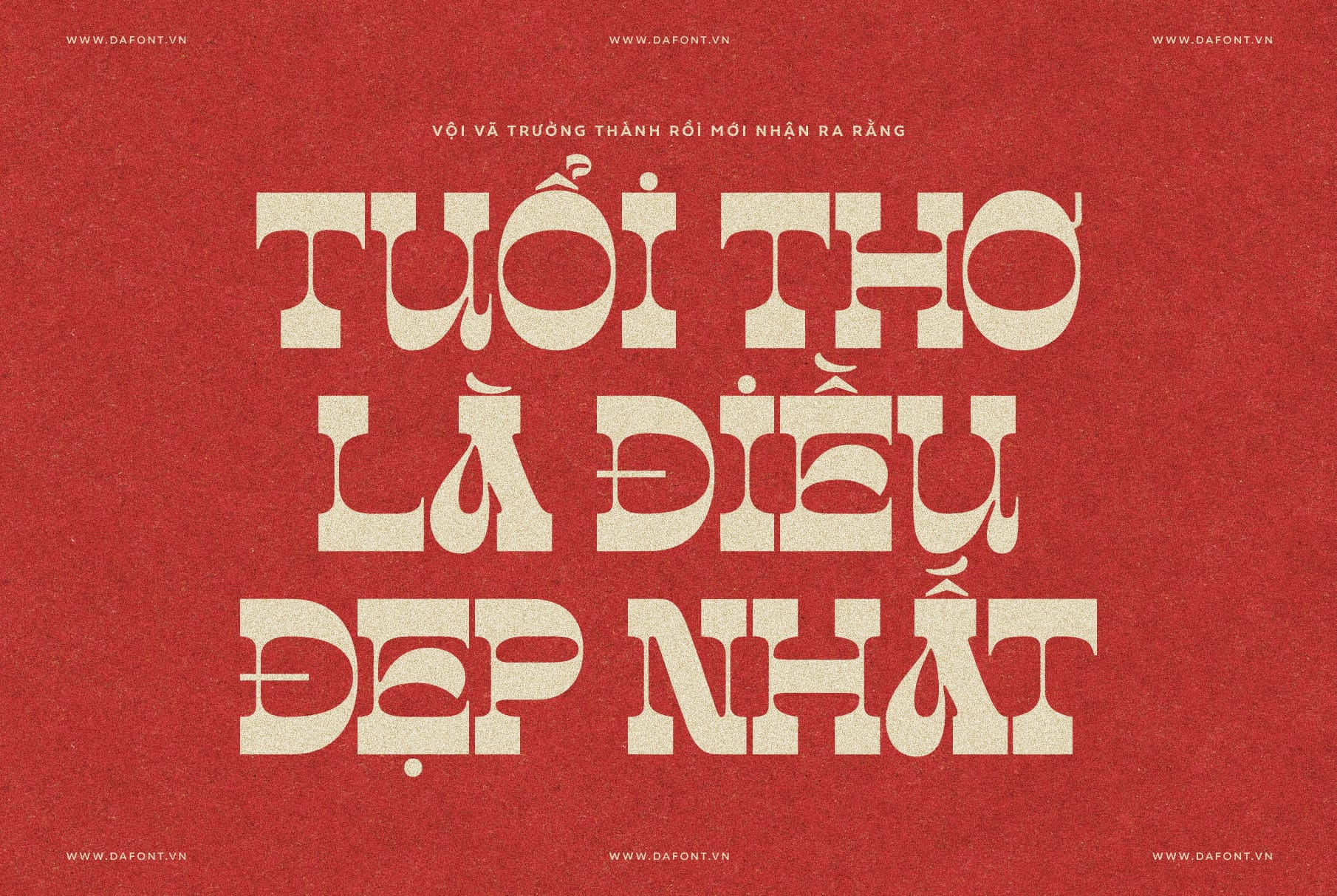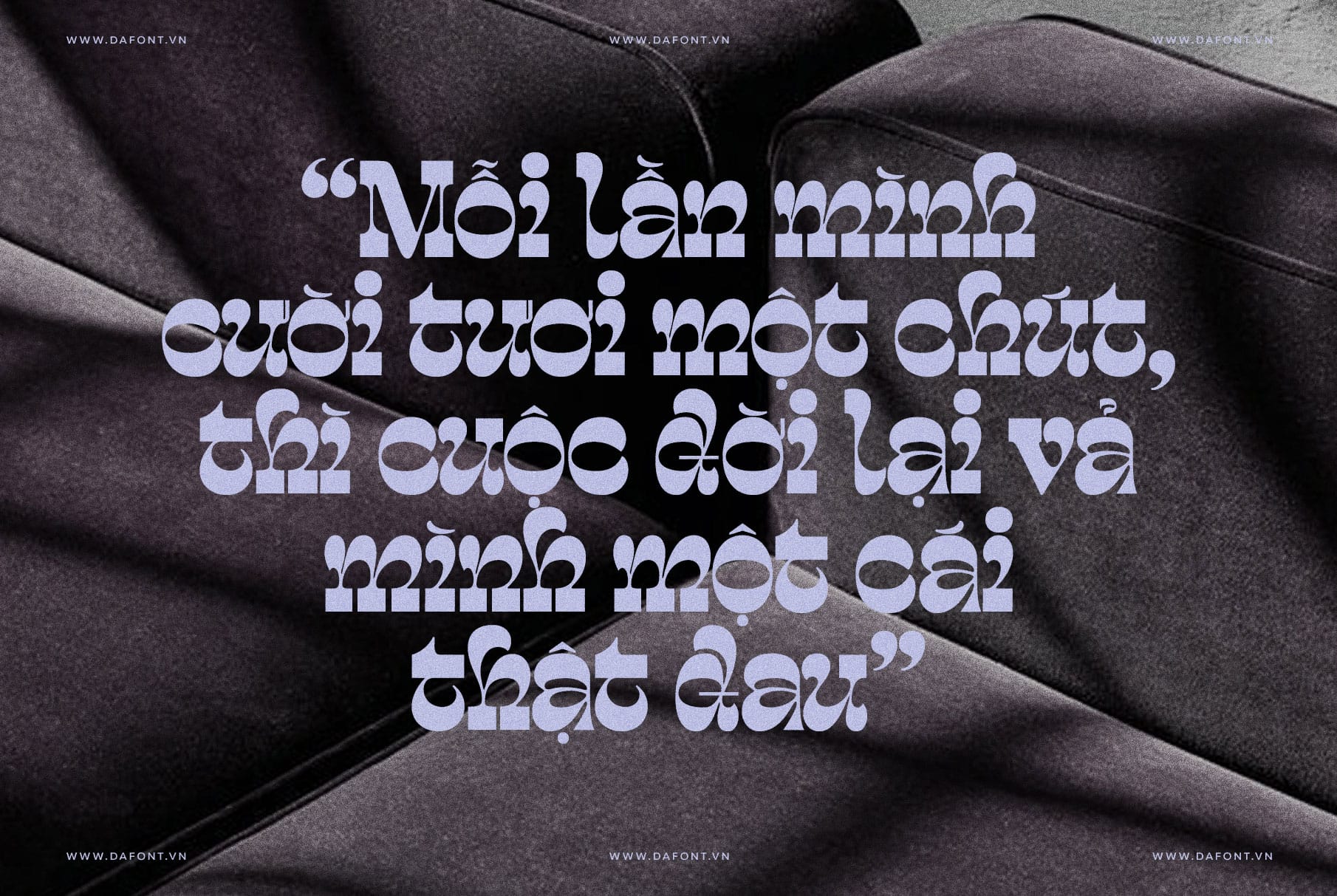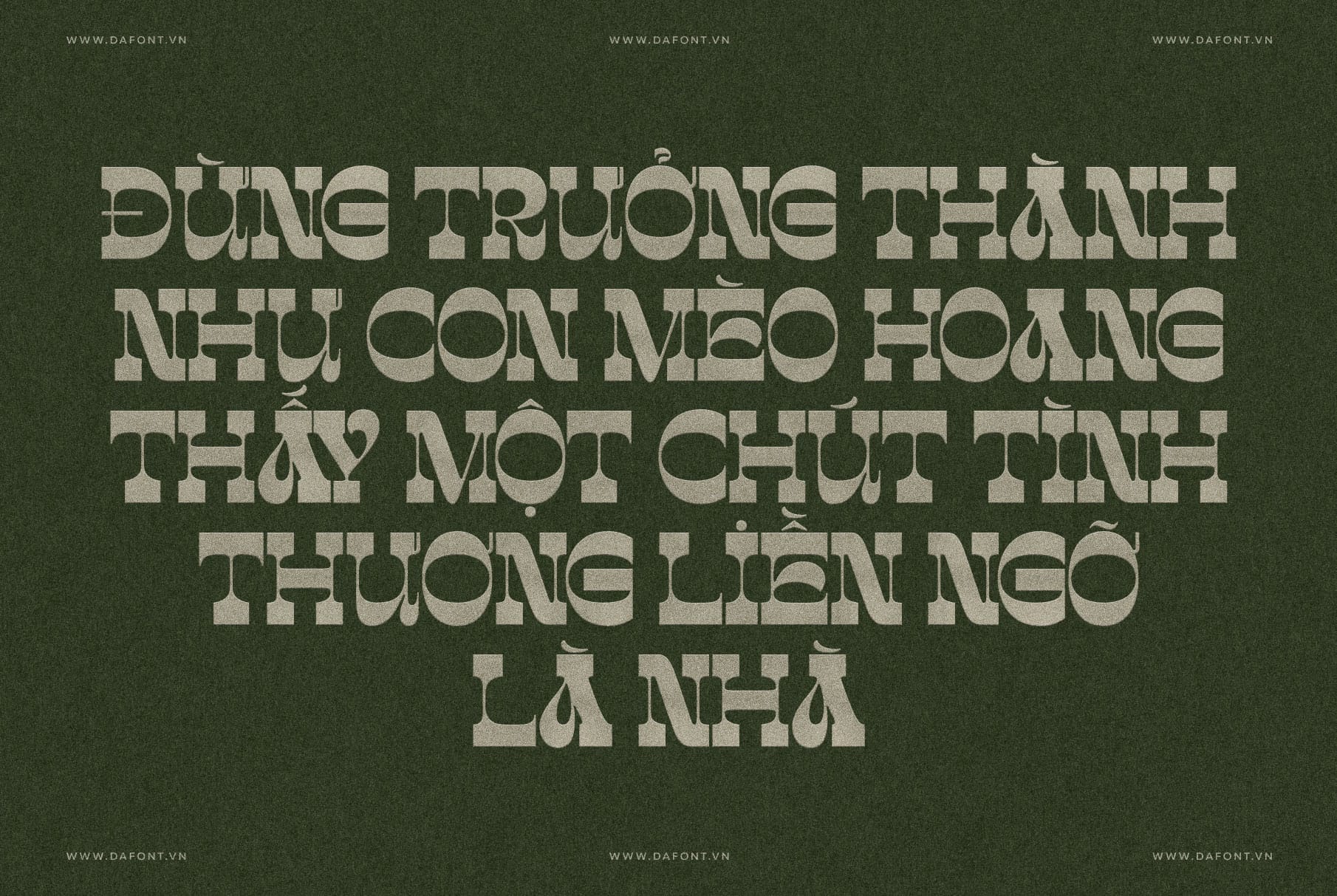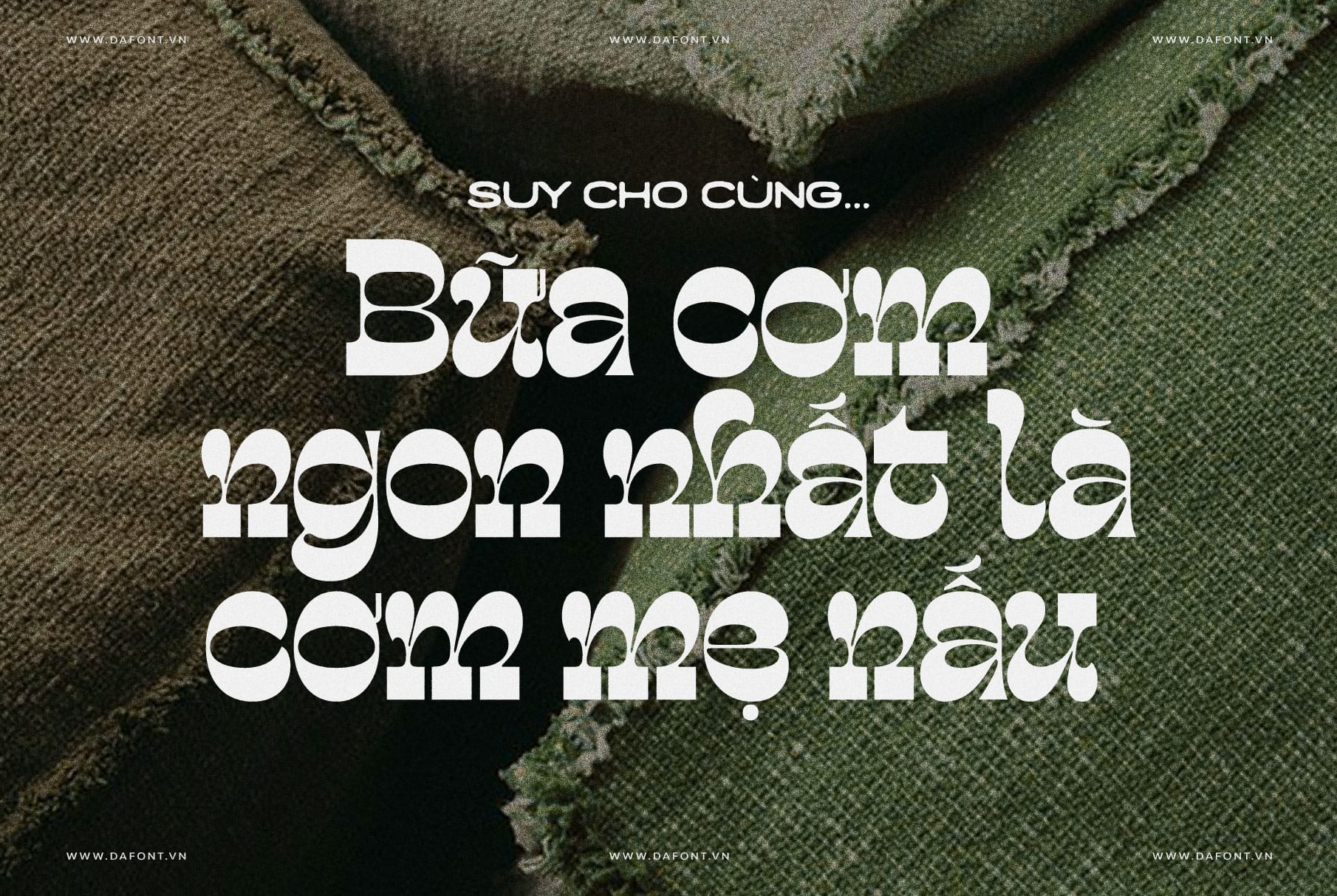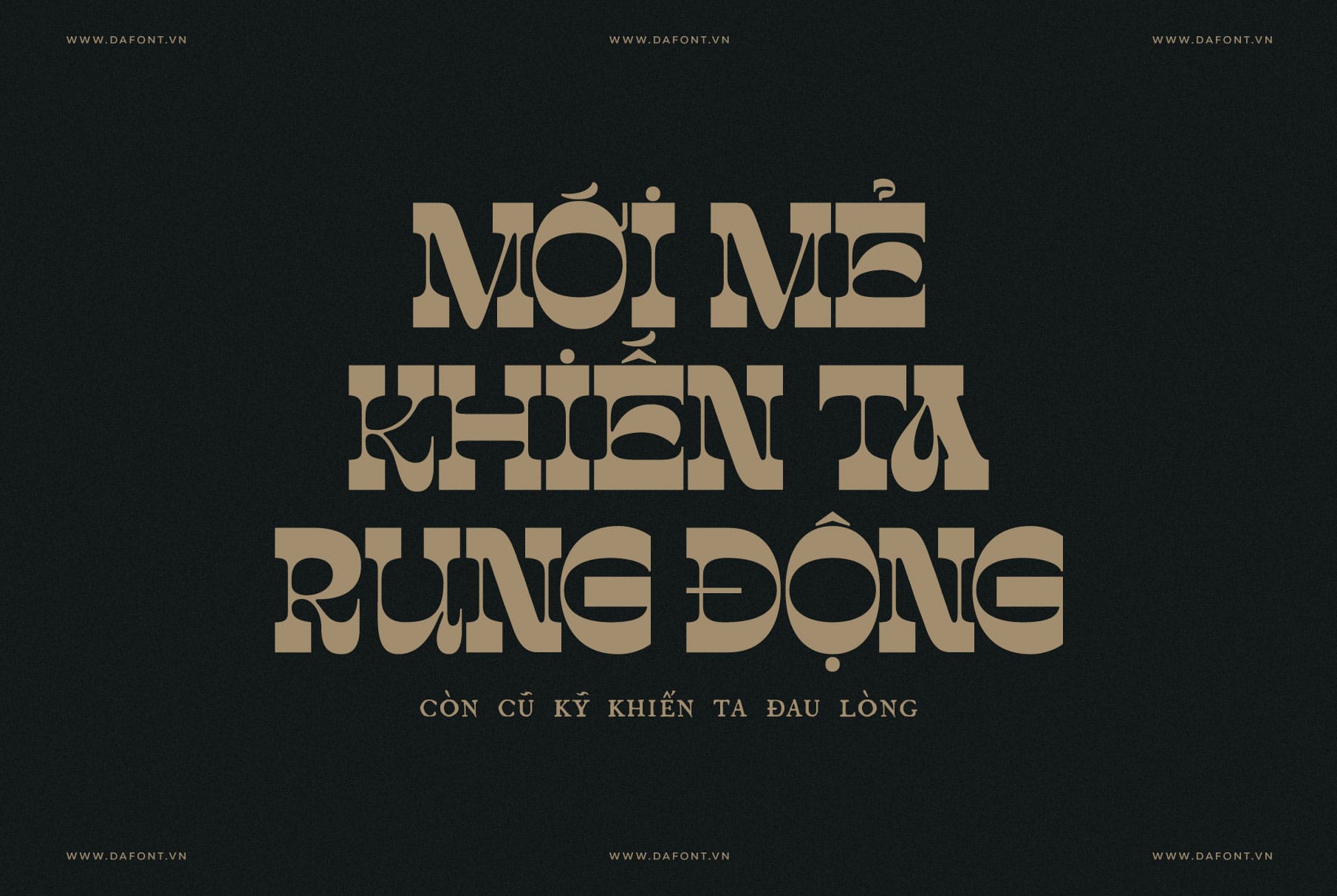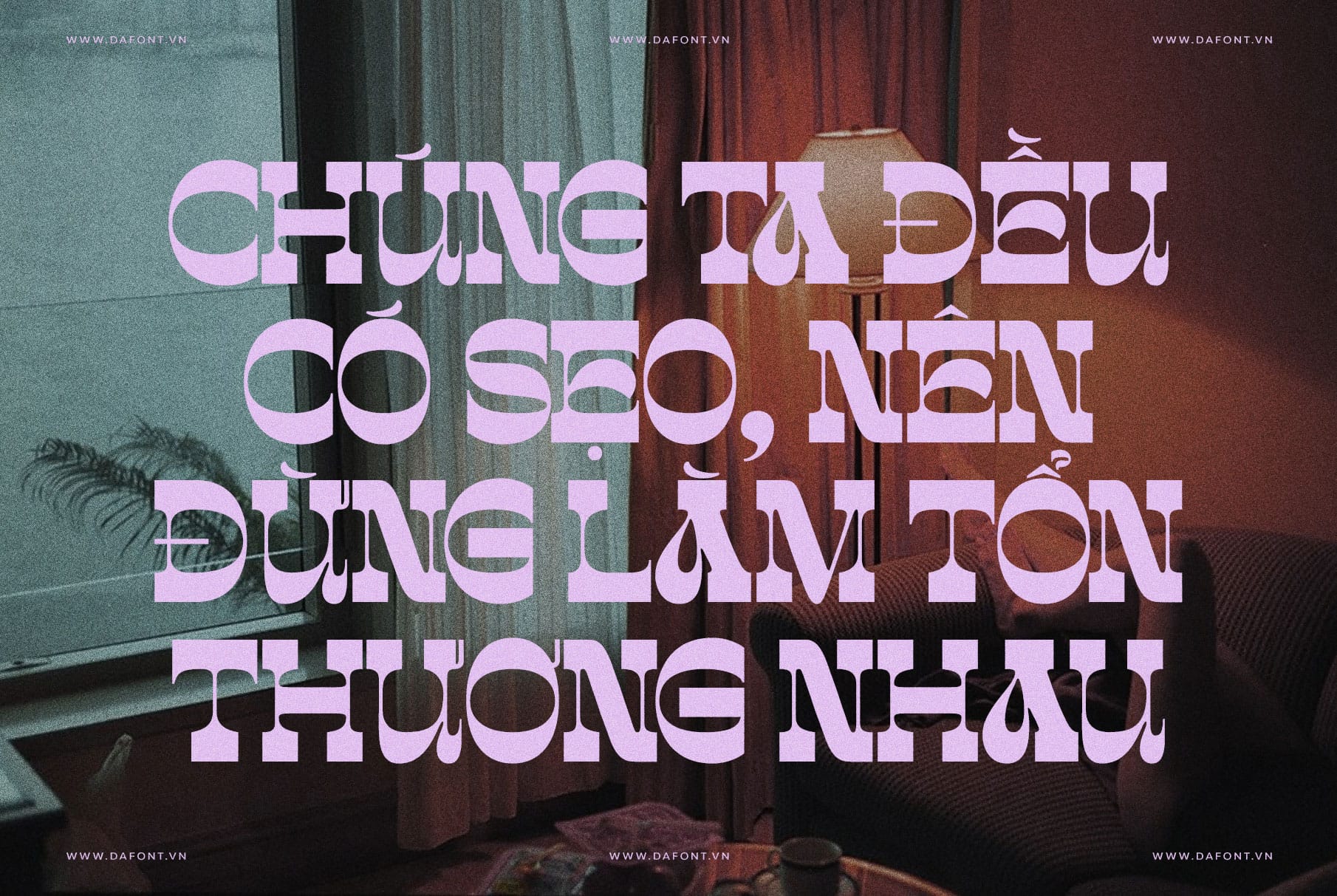
DFVN TAN – MADISON
Kiểu khữ slab serif retro đầy cá tính cho thiết kế hiện đại
DFVN TAN – MADISON font thuộc loại slab serif – kiểu chữ với nét serif vuông vức, dày dặn, tạo cảm giác mạnh mẽ và vững chãi. Điều làm nên sự khác biệt là các đường cong playful (vui tươi), mang đến sự bất ngờ và cá tính. Font gợi nhớ đến văn hóa Mỹ cổ điển: quán soda, đĩa vinyl, hay bưu thiếp du lịch, nhưng vẫn giữ nét hiện đại để phù hợp với branding ngày nay.
Đặc điểm nổi bật DFVN TAN – MADISON
TAN – MADISON là một kiểu chữ slab serif mang đậm phong cách retro và vintage. Không chỉ thu hút bằng vẻ ngoài mạnh mẽ, TAN – MADISON còn mang đến cảm giác hoài cổ nhưng vẫn hiện đại, giúp các nhà thiết kế dễ dàng tạo điểm nhấn trong mỗi dự án sáng tạo.
1. Phong cách slab serif đậm chất retro
TAN – MADISON sở hữu những nét chữ dày, có chân (serif) bản to và vuông vức – tạo cảm giác vững chắc, đáng tin cậy. Phong cách này gợi nhớ đến những thiết kế cổ điển của thập niên 70–80, rất phù hợp với xu hướng retro revival hiện nay.
2. Đường cong mềm mại – mạnh mẽ nhưng không cứng nhắc
Dù mang phong cách slab serif, TAN – MADISON không hề khô cứng. Các đường cong được xử lý tinh tế, giúp font trở nên “playful” (vui tươi) và dễ tiếp cận hơn. Điều này khiến TAN – MADISON vừa mạnh mẽ, vừa mang tính nghệ thuật cao.
Dễ nhận diện thương hiệu
Với độ dày đồng đều và thiết kế độc đáo, DFVN TAN – MADISON font dễ tạo ấn tượng thị giác mạnh mẽ. Đây là lựa chọn tuyệt vời cho logo, tiêu đề, poster, bao bì sản phẩm hay các chiến dịch quảng cáo muốn thể hiện sự khác biệt và cá tính riêng.
Độ tương thích cao trong thiết kế
Font này hoạt động tốt trên cả ấn phẩm in ấn (print) lẫn thiết kế kỹ thuật số (digital). Các nhà thiết kế có thể dùng TAN – MADISON trong các phần mềm như Adobe Illustrator, Photoshop, hoặc Figma mà không lo lỗi hiển thị.
Phong cách kết hợp linh hoạt
DFVN TAN – MADISON phát huy tối đa hiệu quả khi được kết hợp cùng các font sans-serif mảnh như Montserrat, Poppins, hoặc Nexa Pro. Sự tương phản giữa slab serif và sans-serif giúp thiết kế cân bằng, hiện đại và dễ đọc hơn.
Ứng dụng font trong thiết kế
DFVN TAN – MADISON font lý tưởng cho các dự án cần sự hoài cổ nhưng vẫn tươi mới. Dưới đây là một số ứng dụng phổ biến:
• Branding Và Logo: Hoàn hảo cho quán cà phê, cửa hàng vintage, hoặc thương hiệu thời trang retro. Ví dụ, sử dụng font này cho logo sẽ tạo cảm giác ấm áp, gần gũi.
• Poster Và Áp Phích: Với nét bold, font dễ dàng thu hút sự chú ý trong các chiến dịch quảng cáo hoặc sự kiện âm nhạc.
• Thiết Kế Web Và Social Media: Kết hợp với hình ảnh hoài cổ để tạo nội dung hấp dẫn trên Instagram hay Facebook.
• Sản Phẩm In Ấn: Từ bưu thiếp đến bao bì sản phẩm, font mang lại sự chuyên nghiệp và cá tính.
Khi nào nên và không nên sử dụng TAN – MADISON
Nên sử dụng khi:
• Bạn muốn tạo tiêu đề lớn, gây ấn tượng ngay từ cái nhìn đầu.
• Thiết kế logo hoặc thương hiệu cần kiểu chữ có cá tính rõ ràng.
• Poster, ấn phẩm quảng cáo hoặc mạng xã hội cần nổi bật và khác biệt.
Không nên sử dụng khi:
• Văn bản dài hoặc nội dung nhiều – vì kiểu chữ này không tối ưu để đọc nhiều dòng nhỏ.
• Giao diện ứng dụng cần khả năng đọc tốt ở kích thước nhỏ.
• Thiết kế cần phong cách nhẹ nhàng, thanh lịch, minimal – vì slab serif dày thường mang cảm giác mạnh hơn.
Cách kết hợp TAN – MADISON trong thiết kế
• Kết hợp với font sans-serif: Ví dụ bạn dùng TAN – MADISON cho tiêu đề và một font như Helvetica, Montserrat cho phần thân, để tạo sự đối lập và cân bằng.
• Màu sắc & background: Vì chữ dày, nên chọn background đơn giản, tránh quá nhiều texture giúp chữ nổi bật hơn.
• Khoảng cách chữ (letter-spacing) & dòng: Kiều slab serif dày nên cần khoảng “hơi thở” tốt – tăng một chút khoảng cách chữ nếu cần thiết để tránh cảm giác dồn đống.
• Thử nghiệm với hiệu ứng: Vì là font display, bạn có thể thêm chút hiệu ứng đổ bóng, gradient nhẹ hoặc retro filter để tăng cảm giác “vintage”.
DFVN TAN – MADISON Việt hóa là sự kết hợp hoàn hảo giữa sức mạnh thị giác của slab serif và sự uyển chuyển của phong cách retro, mang lại cho thiết kế một bản sắc riêng, ấn tượng và đậm chất nghệ thuật. Đây là lựa chọn lý tưởng cho những ai muốn thương hiệu của mình trở nên nổi bật và đáng nhớ.
Vì sao DFVN TAN – MADISON là font bạn nên thử
Nếu bạn đang tìm một kiểu chữ mang phong cách hoài cổ, mạnh mẽ và có cá tính riêng để làm tiêu đề, logo hoặc ấn phẩm thiết kế – thì DFVN TAN – MADISON chính là lựa chọn đáng cân nhắc. Nhờ phong cách slab serif sáng rõ, các đường nét uốn cong nhẹ nhàng, nó vừa nổi bật vừa mang hơi hướng vintage rất thời thượng.